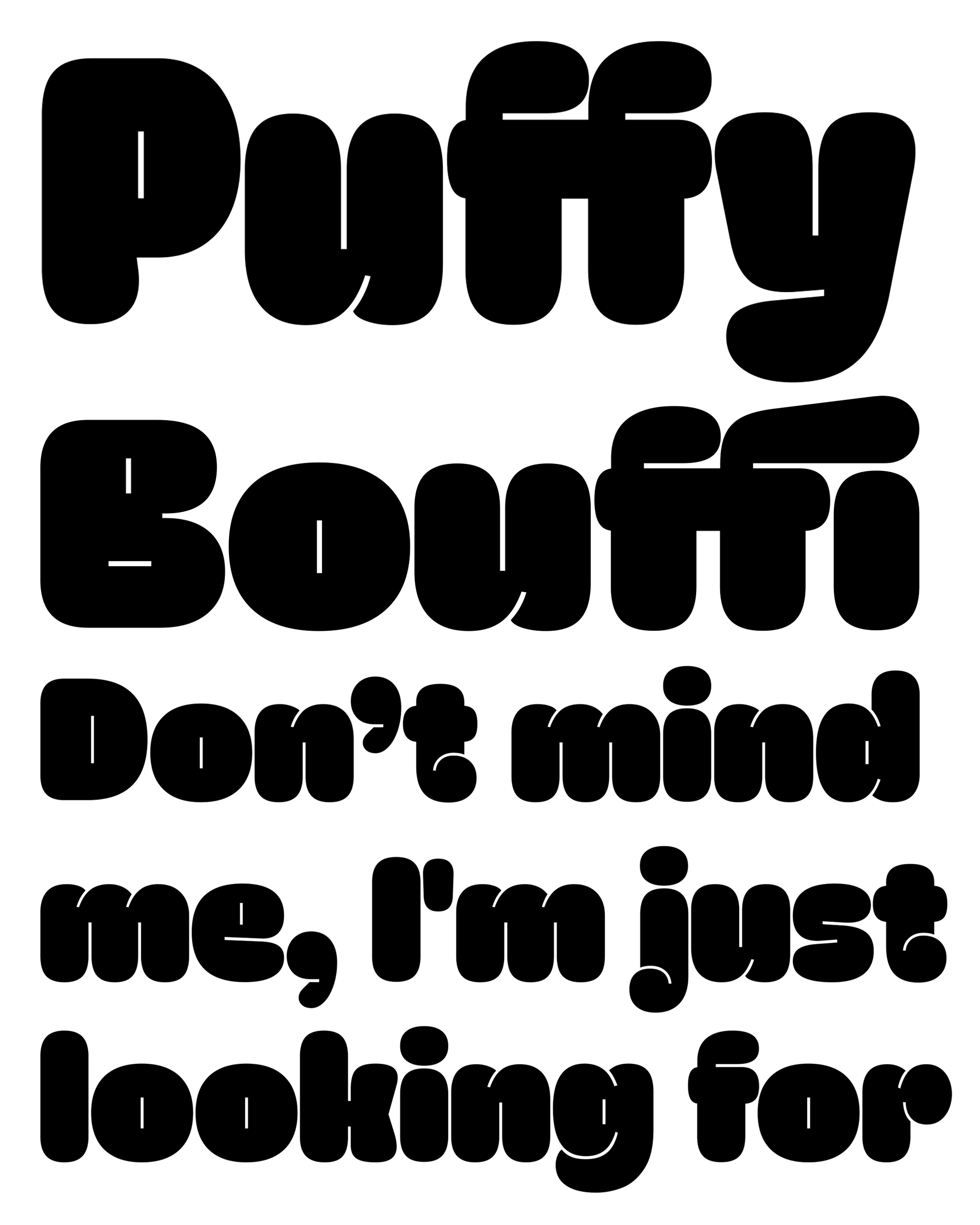
| Descripción | Puffy es una exploración de la suavidad acolchada. Amistosa y blanda, Puffy parece casi una nube. Es tan voluminosa que sus contraformas se reducen a una sola línea. |